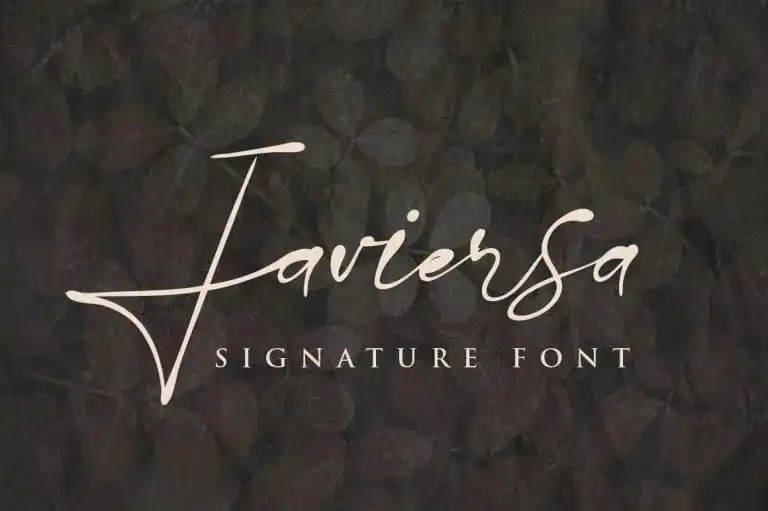
Javiersa Handwritten Font – Download Grátis
Introduzimos Javiersa Handwritten Font, uma fonte de escrita a mão romântica com muita personalidade. Esta elegante fonte está perfeitamente adaptada para criar um toque personalizado nas mais diversas áreas do design gráfico. Ela brilha sob os mais diversos tipos de projetos: desde convites de casamento, cartões de agradecimento e cartas pessoais até logotipos e cartões de visitas. Javiersa Handwritten é uma fonte ideal para estilos gráficos que valorizam um toque único e delicado. Suas linhas suaves, os gílios belos e alternativas memoráveis a tornam uma escolha perfeita para qualquer projeto que se destine a transmitir o seu mais autêntico tom de voz visualmente. Javiersa Handwritten Font é um recurso gráfico convidativo para designers buscando dar vida aos seus projetos com elegância e carisma.